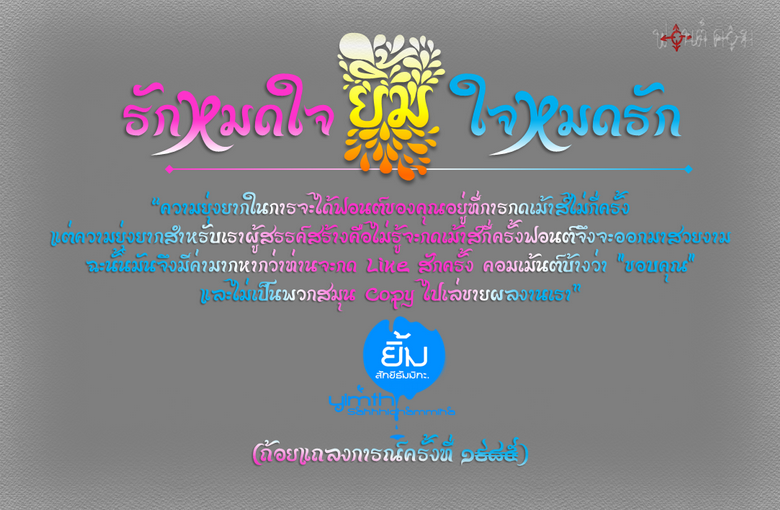
บักหำแหล้ อยากขี้เหร่...
หลังจากนั่งทำฟอนนี้มาทั้งคืน + ทั้งวัน แล้วมันอยากขี้เหร่ครับ
iannnnn จะเอาไปแปะเป็นแถลงการณ์ก็ได้นะครับ แค่ลองทำ ๆ ดู
เลยได้โลโก้ใหม่ให้กับตัวเองอีกหนึ่งตัว... :43:
ลองเอาฝรั่งมาโซว์ลองดูดิ
แหล่ม..มั๊ย
แรงบันดานใจมาจาก Poster นี้ครับ
กับนี่ครับ
แต่ตัว X ผมตั้งใจทำให้ใช้เป็น ห ได้ตามแบบของหนังเรื่องนี้ครับ
ตั้งใจทำคำว่า "เหลือ" เหมือนกันแต่ตอนนี้เตรียมตัวสอบอยู่ครับเอาไว้ทำทีหลัง
สังเกตฟอนต์ดิสเพลย์ของป้ายหนัง เหลือแหล่ เป็นตัวเดียวกะหนัง Love Not Yet...
โห แรงบันดาลใจมาจากแถวนี้ทั้งนั้นเลย :25:
สวยมากก ๆ เชียร์  ถ้าเอาไปใช้ขึ้น Display งานไทยๆ นี้สวยเลยมาก เลยนะ แนวดี   :45:
มาจากคุณนั่นละครับ แหม...แกล้งทำลืม